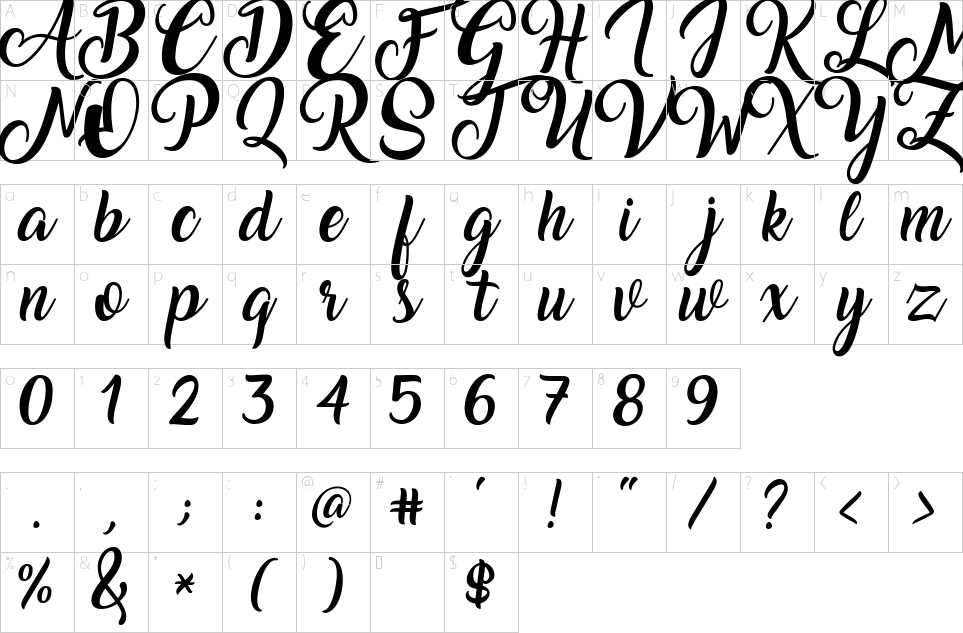
Amarillo é uma fonte gráfica que traz um toque leve e alegre à sua composição de texto. Desenvolvida por Francis Studio, esta fonte tem uma aparência fluida e sofisticada, adequada para uma variedade de projetos, desde materiais educativos até design gráfico de moda. Com um estilo contemporâneo e uma proporção equilibrada, Amarillo combina facilmente com outros tipos de fontes, tornando-a uma escolha inteligente para designers que desejam um visual atraente e moderno em seus projetos. Com mais de 298.000 downloads, é evidente que muitos designers compartilham do mesmo entusiasmo por este design limpo e versátil. Descubra por si mesmo o poder de Amarillo para transformar seus documentos e materiais em algo ainda mais especial.